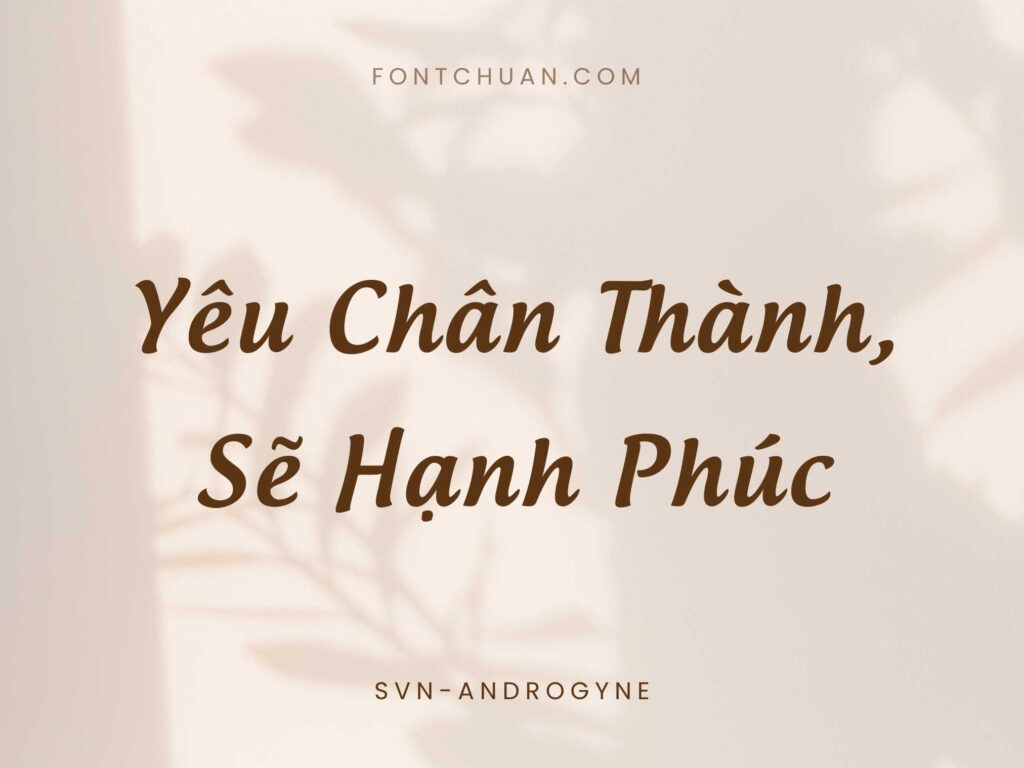
Font SVN Androgyne Việt Hóa
Androgyne là một font chữ thuộc thể loại script, được thiết kế bởi Dimitri Castrique và phát hành lần đầu vào năm 2009. Font này mang phong cách viết tay độc đáo, kết hợp giữa sự mềm mại và mạnh mẽ, tạo nên sự cân bằng hài hòa giữa các yếu tố nam tính và nữ tính. Với 145 glyphs và 230 ký tự, Androgyne hỗ trợ nhiều ngôn ngữ khác nhau, giúp mở rộng phạm vi sử dụng trên toàn cầu. Font đã được Việt hóa để hỗ trợ tiếng Việt bởi Styleno.1 Fonts, đồng thời được thành viên của Font Chuẩn sưu tầm và chia sẻ, đáp ứng nhu cầu của bạn đọc và ứng dụng thực tế vào các dự án thiết kế.
Đặc điểm thiết kế của Androgyne bao gồm các đường nét uyển chuyển, linh hoạt và độc đáo, tạo cảm giác như chữ viết tay thực sự. Font này phù hợp cho các ứng dụng như thiết kế logo, tiêu đề, thiệp mời, áo thun và các dự án sáng tạo khác. Các ngành nghề phù hợp bao gồm quảng cáo, sự kiện, thời trang, làm đẹp và nghệ thuật.